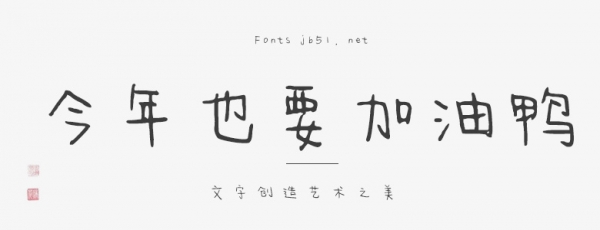
今年也要加油鴨是三極字庫(kù)推出的第五款免費(fèi)商用手寫字體,具有溫柔、婉約、手寫風(fēng)、簡(jiǎn)約 的風(fēng)格,可以滿足您設(shè)計(jì)上的各種需求,該字體主要用于海報(bào)企宣、書籍、店鋪、活動(dòng)、健康養(yǎng)生 等場(chǎng)景。